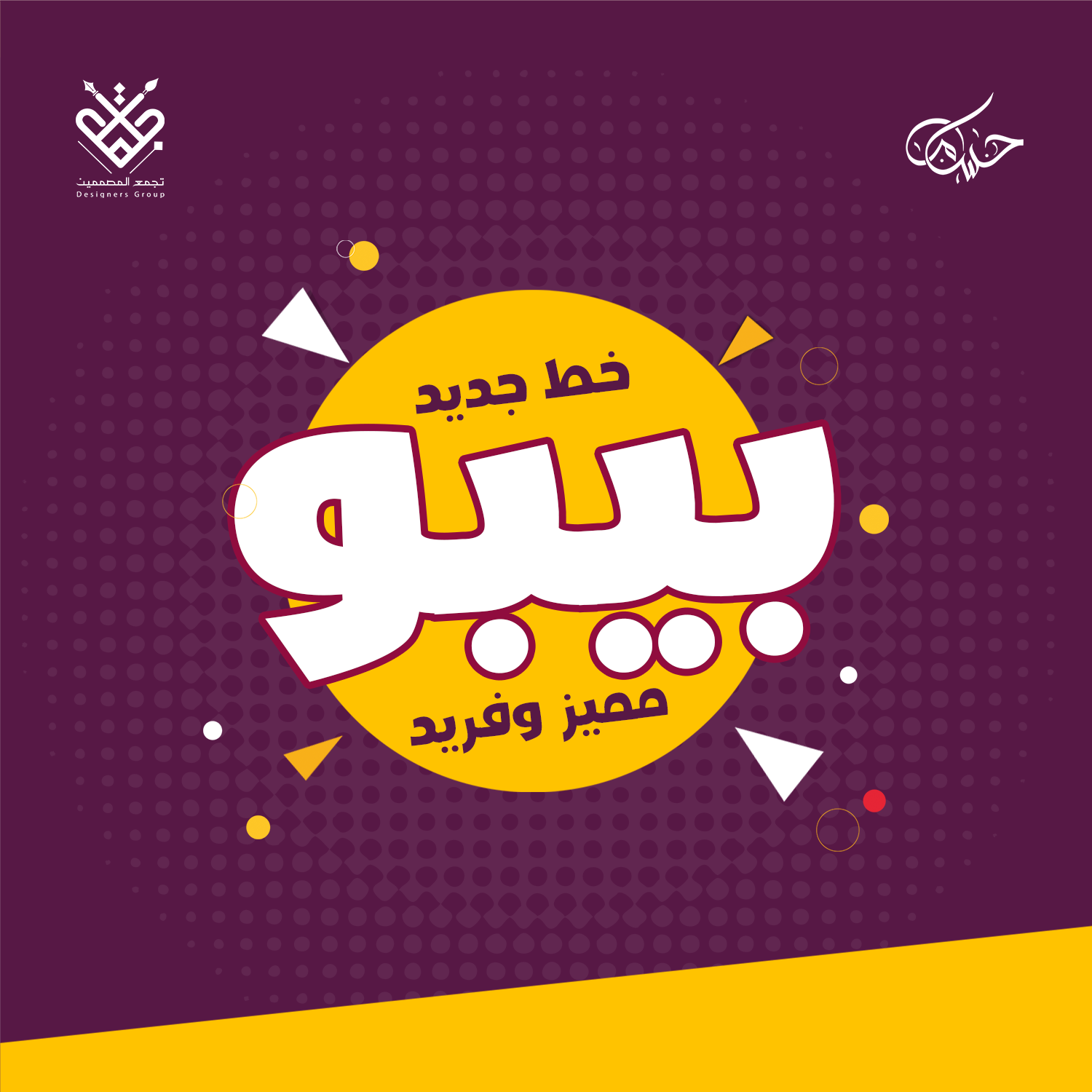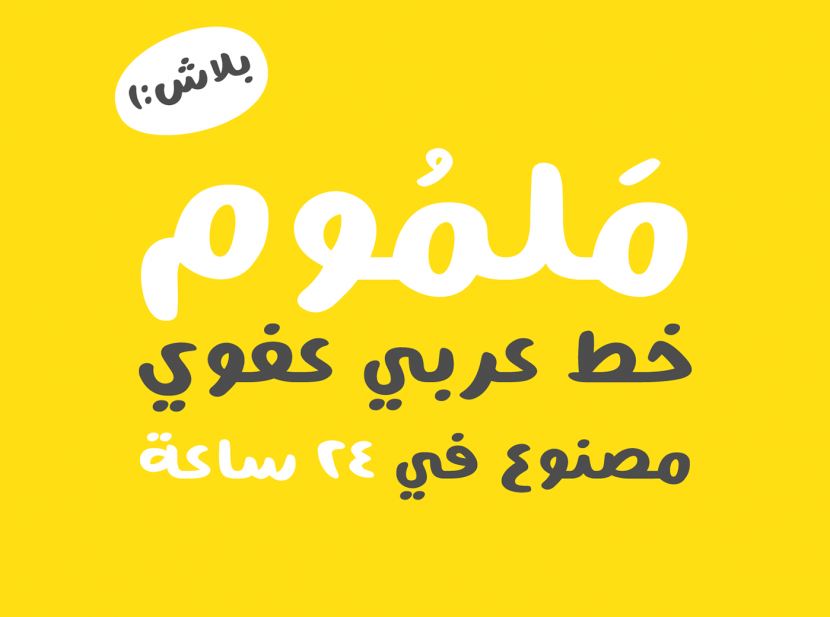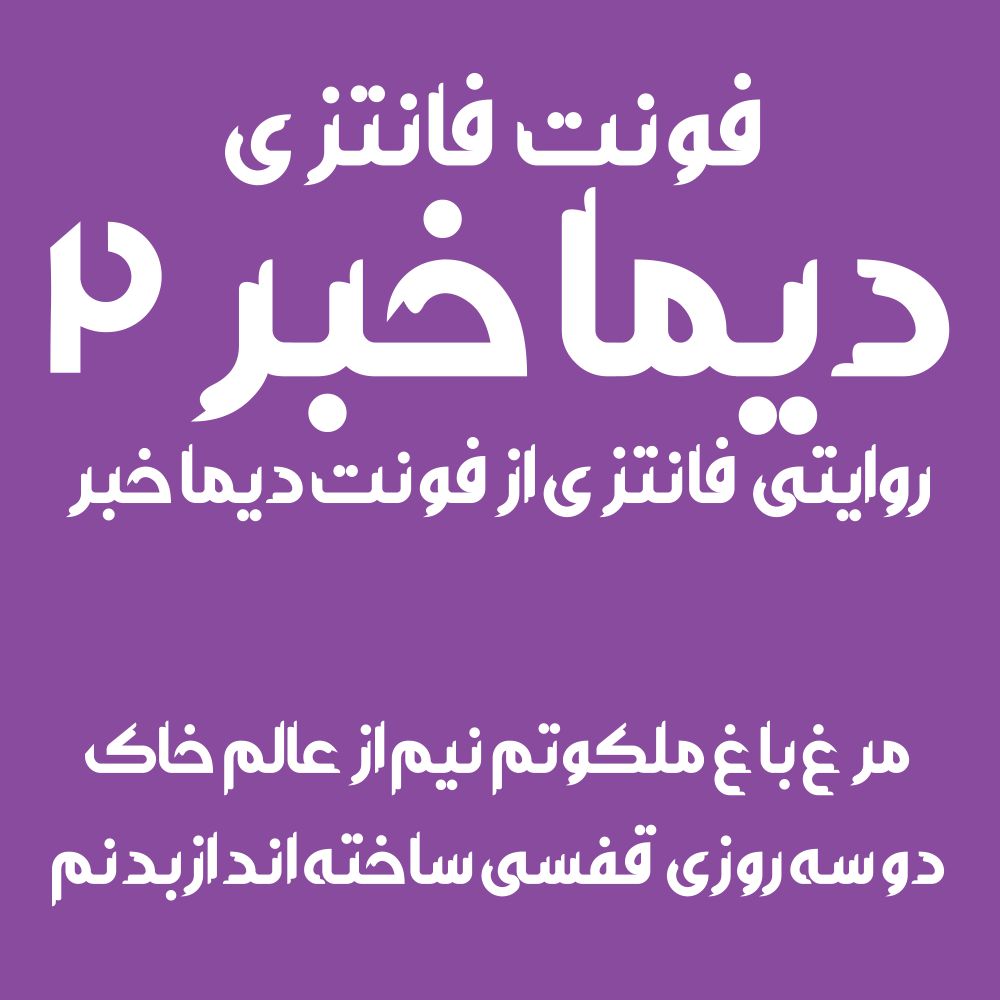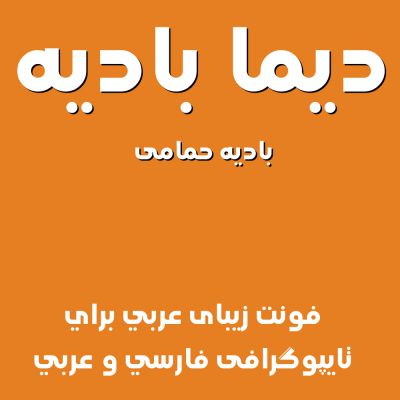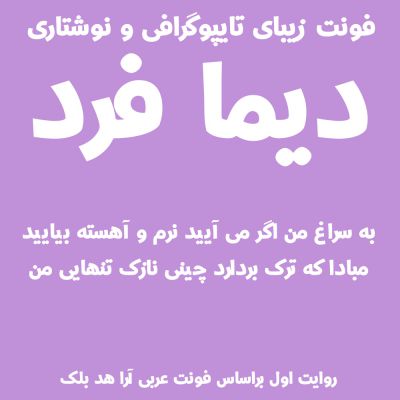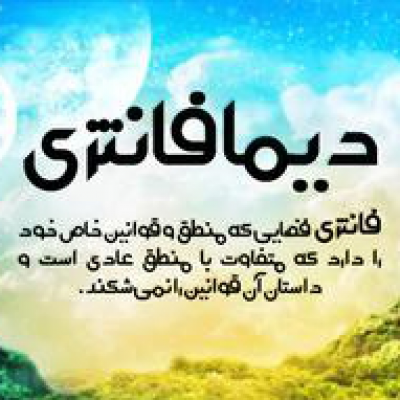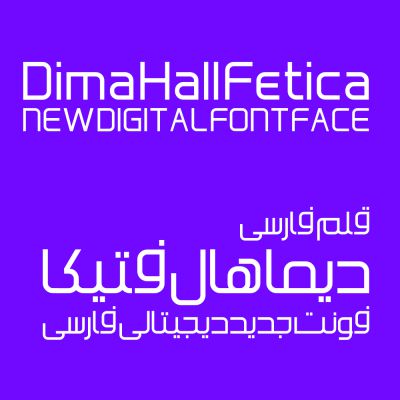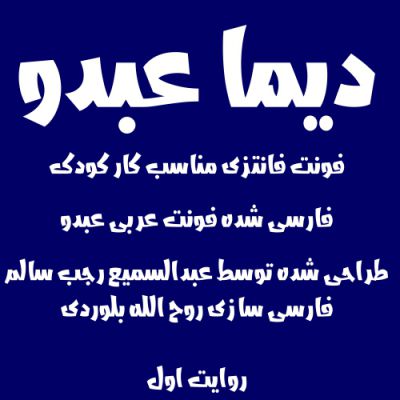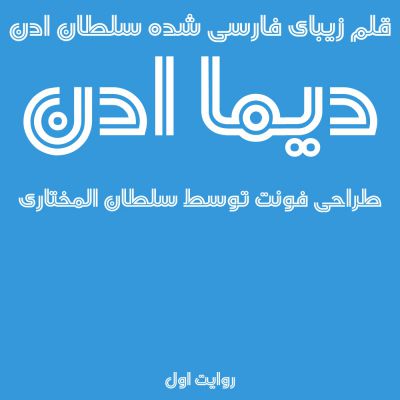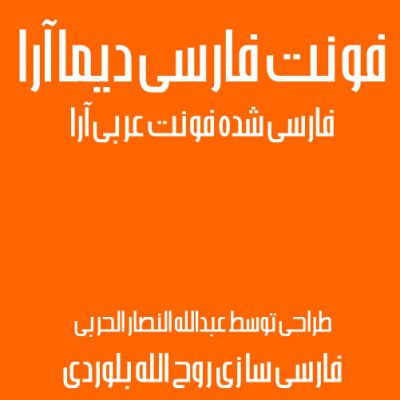
قلم جواد یک فونت کوفی عربی است که از زبان فارسی هم پشتیبانی می کند...
فونت رفیع یک فونت بر پایه کوفی است که از زبان فارسی پشتیبانی می کند....
یک فونت مستطیلی با پشتیبانی از زبان فارسی...
فونت اقلام یک فونت عربی است که از زبان فارسی نیز پشتیبانی می کند. این فونت با خطوط تیز حالتی خاص را به مخاطب منتقل می کند/...
قلم خاص و زیبای سنباد برای طراحی لوگوهای خاص با فونت نازک و زیبا کاربرد دارد....
قلم زیبا و نو آورانه ایر استریپ عربی بسیار زیبا و مناسب کارهای دیجیتال می باشد. این قلم توسط ابراهیم حمیدی و عبدالله عارف طراحی شده است....
قلم زیبای جزیل با حرکت های زیبا و پشتیبانی از زبان فارسی یک فونت مناسب طراحی لوگوتایپ می باشد....
این قلم یک قلم متفاوت عربی و انگلیسی برای طراحی لوگوتایپ می باشد....
دیما پونه نسخه فارسی شده وزن ضخیم فونت عربی تاجاول می باشد. این فونت مناسب طراحی لوگو ، تابلو و سایر تیتر های درشت و زیباست....
این قلم زیبای رایگان عربی در 10 وزن متفاوت منتشر شده است. این قلم بسیار کاربردی و در اوزان مختلف زیباست....
دیما غریب نسخه فارسی شده فونت عربی دیما غریب است که ظاهری عاشقانه دارد....
قلم زیبای عربی دی جی غریب از سری فونت های دی جی عربی است که مناسب تابلو و عناوین بزرگ می باشد. در دو زن ساده و ضخیم منتشر شده است....
دیما البوباه یا دیما جام فونت زیبای کودکانه است که بر پایه فونت عربی البوباه طراحی شده است. فونت اصلی فقط 16 گلیف را بیشتر طراحی نکرده بو...
دیما یکان بی ار ویرایشی از فونت دیما یکان حرفه ای نسخه ضخیم می باشد که برای طراحی لوگو تایپ یا نام کتاب و مجله کاربرد دارد....
قلم زیبای دیما یکان حرفه ای نسخه ضخیم سومین وزن از فونت دیما یکان حرفه ای می باشد که بهمراه دو وزن قبلی برای وب و سایر کاربردها قابل استف...
دیما یکان حرفه ای ریگولار دومین وزن از فونت زیبای دیما یکان حرفه ای با وزن 400 مناسب وب سایت و نرم افزارهای موبایل است....
دیما یکان حرفه ای نازک ، نازک ترین فونت ایرانی برای استفاده در دستگاههای برش خطی و برش لیزر نازک حکاکی های ریز و وب نیز می باشد. این فونت...
با توجه به استقبال دوستان از فونت دیما یکان و سری های متفاوت این فونت تصمیم گرفتیم آنها را در یک بسته 36 فرمتی که شامل 6 خانواده فونت یکا...
قلم استاد عبدو قلمی زیبا با پایه خط کوفی با نو آوری های زیبا و پشتیبانی کامل از زبان فارسی در 14 وزن متفاوت ارایه شده است....
دیما غایت فونت دست نویس زیبای فانتزی فارسی شده فونت عربی غایت می باشد این فونت برای کاربری هایی اعم از لوگوتایپ نام کتاب و پوستر کتاب کود...
کو تکست از سری قلم های مناسب وب و تایپ و تحریر است. این فونت در چندین وزن مختلف برای شما قرار داده شده است....
قلم دی جی فاياتي قلم زیبای عربی است که در چند وزن ارایه شده است. این فونت جنبه فانتزی دارد....
قلم دیما جی یی فارسی شده فونت جی یی کپ مدیوم است که از خط کوفی الهام گرفته شده است....
نیشان یک نوع منحصر به فرد است که روح کتیبه های باستانی کوفی را با ظرافت در نوشتارهای معاصر عربی ادغام می کند. حروف با تفاوت شدید در ابعاد...
قلم دیما یاسین براساس قلم عربی با همین نام ایجاد شده است.برای این قلم زبان فارسی کاراکترهای لازم را باز بینی و طراحی و اصلاح شده و قراردا...
قلم زیبای عربی برای طراحی و تابلو سازی بسیار مناسب است در چند وزن متفاوت و زیبا...
فونت فونت روس روزايك در سه وزن به زبان عربی منتشر شده است. این فونت ظاهری فانتزی دارد....
قلم رایگان شارب یک قلم رایگان عربی سنگین وزن است. این قلم ظاهر شاد دارد و برای تیتر های خاص یا لوگوتایپ مناسب است....
فونت فارسی صندل(Sandal Typeface)نسخه دستکاری و فارسی شده یک قلم دکوراتیو و فانتزی عربی است که حالت هندسی و مرتب آن انتخاب مناسبی برای لوگ...
قلم عربی در 5 وزن زیبا برای استفاده رایگان منتشر شده است....
این قلم بسیار زیبا برای مراکز دانشگاهی طراحی شده است. طراحی زیبا و منظم و چشم نواز این فونت برای هر نوع کاری مناسب است. این قلم توسط افرا...
این فونت یک فونت رایگان در 5 وزن متفاوت است که بسیار زیبا و کاربردی است....
قلم زیبای ارابوتو یک قلم زیبای عربی است که در 6 وزن متفاوت منتشر شده است. این قلم زیبا مناسب پوستر سازی و لوگوتایپ میباشد....
دیما جوهره فارسی شده فونت الجوهره عربی است که اصلاحاتی مثل اتصالات بین حروف را افزودیم.این قلم توسط یاثر تاج طراح عرب طراحی شده است....
قلم شاد دجلی تاچکیلی (دجادلي تاتشكيلي) یک قلم بسیار زیبای شاد می باشد که در دو نسخه پر و تو خالی منتشر شده است....
قلم زیبای دست نویس انامیل یک قلم رایگان عربی است که برای نگارش و طراحی متن های شاد و کودکانه مناسب است....
قلم زیبای عربی موتكن نوكته با ضخامت زیاد برای تیتر های خاص کاربرد دارد....
این قلم زیبا در چهار وزن متفاوت توسط تارک الشوا طراح عرب طراحی شده است و ظاهری فانتزی و دیجیتال دارد....
قلم زیبای ملموم توسط فهد الفریخ طراح عرب طراحی و ایجاد شده است. این فونت رایگان است و ظاهری شاد و شیرین دارد....
قلم زیبای دریم عربی با پشتیبانی از زبان فارسی در ۸ وزن متفاوت رایگان دانلود کنید....
این فونت عربی چند زبانه برای فارسی نیز قابل استفاده است. تنوع زیاد اوزان فونت از امکانات این فونت است....
فونت فارسی دیما عبدو فارسی شده فونت عربی عبدو می باشد که توسط عبدالسمیع رجب سالم طراحی و اجرا شده ٬ این فونت توسط روح الله بلوردی فارسی س...
این قلم فارسی سازی شده فونت عربی کات می باشد ٫ پایه طراحی قلم خط کوفی می باشد. ظاهر زیبا و استایل متفاوت هم برای طراحی مناسب است هم برای ...
فونت عربی آرا جز فونت های جدید عربی است که مناسب طراحی لوگو تایپ می باشد٫ طراح این فونت عبدالله الحربی طراحی سوری می باشد. ما این فونت را...
تایپوگرافی کاری سخت و طاقت فرساست و نیاز به ذوق و علاقه زیاد و همچینین وقت بسیار است ، اما اکنون با آمدن فونت های جدید این کار ساده تر شد...
فونت زیبای Motken daeira فونتی کاربردی برای طراحی و تایپوگرافی می باشد. اما دوایر اضافی و نداشتن ترکیب های فارسی مشکل بزرگ این فونت است ،...
فونت سوگند یک فونت فارسی فانتزی و جذاب است که برای خط فارسی توسط حسین تقیزاده طراحی شده است. موارد کاربری آن را میتوان هرجایی که باید ا...
قلم فارسی یکان از قلم فارسی های ممتاز فارسی است که کاربردهای بسیار زیادی در طراحی کتاب و پوستر دارد. از این قلم فارسی در کارهای رسمی متدا...